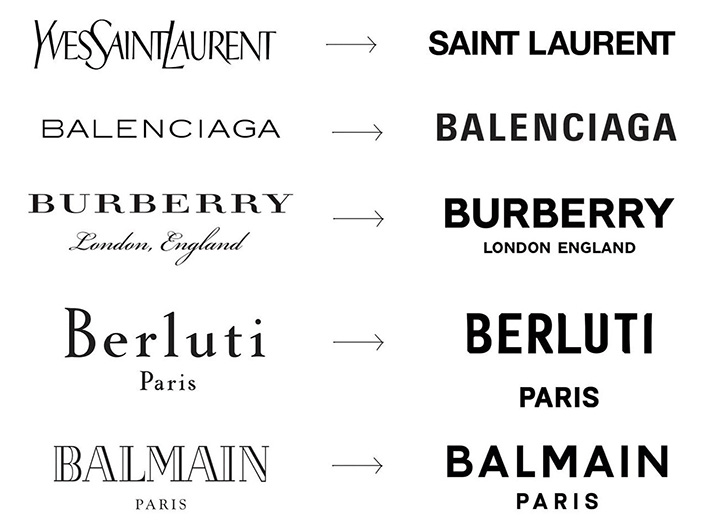
Logotypy kultowych marek
Coraz częściej możemy spotkać się z rebrandingiem znanych firm, które opiera się na maksymalnie uproszczonym logotypie. Boom na tego typu zabiegi rozpoczęła branża modowa. Nie tylko ogólnodostępne sieciówki, ale też bardziej luksusowe domy mody, których znaki firmowe były świetnie rozpoznawalne na rynku nieoczekiwanie zmieniały wygląd logo. Wkrótce większość znanych marek sygnowała swoje produkty znakiem, który był bardzo słabo rozpoznawalny na tle konkurencji.
Dlaczego firmy, których logo były tak charakterystyczne, że niemal stanowiły symbol luksusu w świecie mody zdecydowały się na ten krok?
Zabiegi upraszczania logotypów są wymogiem czasów. Obecnie dobrze zaprojektowane logo musi być czytelne zarówno w druku jak i na ekranach urządzeń elektronicznych. A te, nie ułatwiają projektantom pracy. Różne wielkości ekranów, starsze urządzenia, gdzie jakość wyświetlanych obrazów jest nieco słabsza, a także nieunikniony problem z prezentowaniem przez osoby postronne logotypu zapisanego w słabej jakości pliku. Dodatkowym atutem jest fakt, że tego typu projekty świetnie sprawdzają się zarówno na reklamach wielkoformatowych jak i małych metkach przyszytych do ubrań. Proste, jednobarwne litery będą także dobrze komponowały się zarówno z kolorowymi, lekkimi reklamami promującymi kolekcje wiosenne jak i z tymi zimowymi, które mają zupełnie inny charakter.
Trendowi maksymalnego upraszczania logo poddały się wkrótce także marki z innych branż - Google, Airbnnb, Uber, Microsoft, Premier League… Wymieniać można by długo. Wiele z nich postawiło na charakterystyczny kolor, nadając mu status symbolu marki.
Choć na pierwszy rzut oka nowoczesne logotypy są do siebie bardzo podobne, to jednak trudno je ze sobą pomylić. Drobne szczegóły w kształcie liter, ich wysokości, odstępy miedzy nimi itp. sprawiają, że każdy z projektów ma swój charakter. Także kontekst i otoczenie, w jakim pojawia się projekt nie jest bez znaczenia. Choć np. Samsung i Balenciaga promują swoje produkty logo o podobnym kroju pisma, trudno jest je ze sobą pomylić. Nie spodziewamy się przecież na obudowie ekranu komputera znaleźć logo domu mody.
Tego typu zabiegi są przyjemnym powiewem świeżości i oddechem po przepełnionych pstrokatymi kolorami i wymyślnymi literami projektach, które tak popularne były w poprzednich latach. Jednak zanim zastosujemy tego typu pismo w logo naszej firmy, zastanówmy się, czy spełni ono swoje zadanie, czy tego typu działania sprzyjają jedynie największym graczom na rynku?